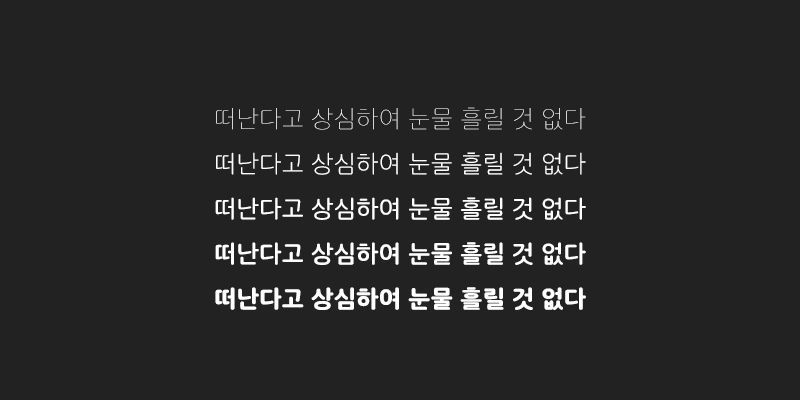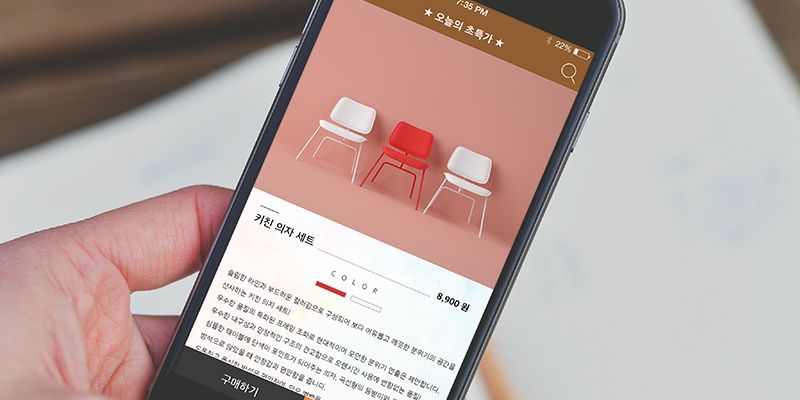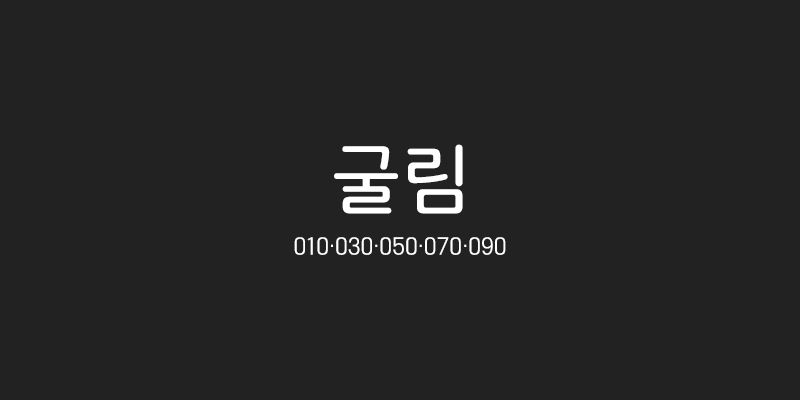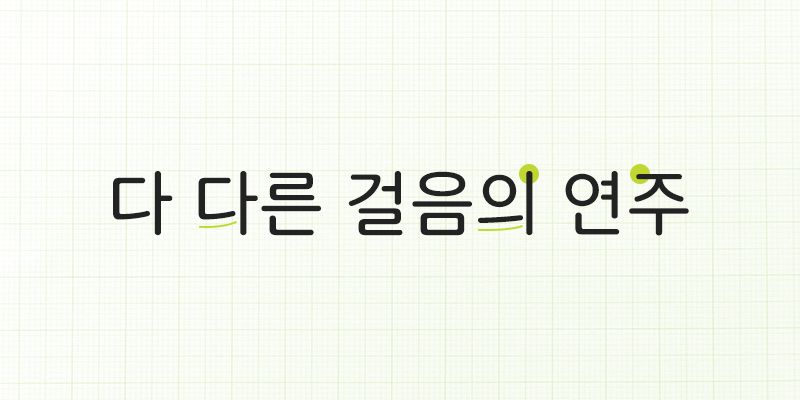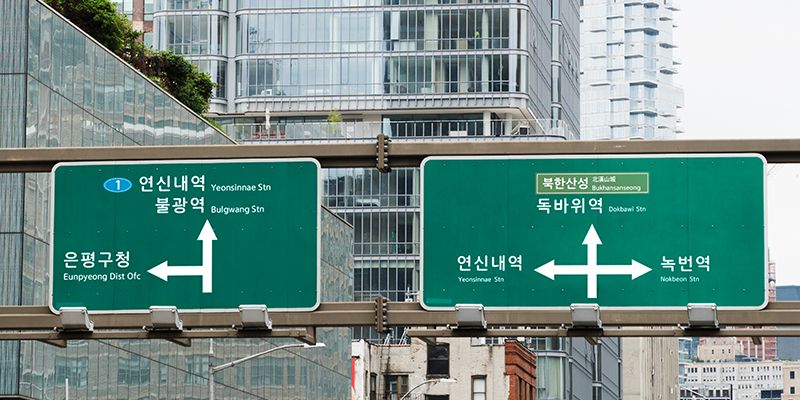
210 Gulim ist eine Schriftfamilie, bei der die Lesbarkeit im Vordergrund steht. Sie zeichnet sich durch abgerundete Strichabschlüsse und ausgewogene Proportionen aus, die in jeder Art von Schriftsatz für Stabilität sorgen. Jedes Zeichen wurde sorgfältig entworfen, um die Lesbarkeit durch eine optimale Raumaufteilung zu verbessern.